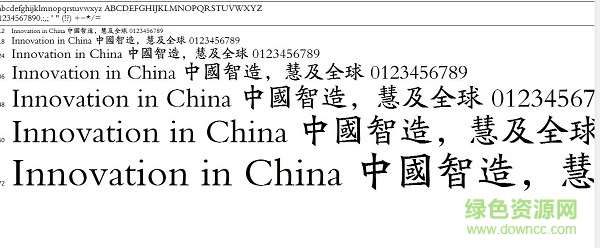
楷書繁體字體包
繁體楷書字體大全是本站為需要的朋友整理的楷書字體合集,包含了和平楷書、白舟細(xì)楷書、方正北魏楷書繁體、硬筆楷書繁體等一系列繁體字體,每一款制作都很不錯(cuò),適用范圍廣,有需要者歡迎免費(fèi)下載!
楷書介紹
【魏】
北派書體,帶著漢隸的遺型,筆法古拙勁正,而風(fēng)格質(zhì)樸方嚴(yán),長(zhǎng)于榜書,這就是所說的魏碑。南派書法,多疏放妍妙,長(zhǎng)于尺牘。
【唐】
唐代的楷書,亦如唐代國(guó)勢(shì)的興盛局面,真所謂空前。書體成熟,書家輩出,在楷書方面,唐初的虞世南、歐陽(yáng)詢、褚遂良、中唐的顏真卿、晚唐的柳公權(quán),其楷書作品均為后世所重,奉為習(xí)字的模范。
【宋元】
唐代楷書法度森嚴(yán)、結(jié)構(gòu)嚴(yán)謹(jǐn),到了宋元時(shí)期書法家們開始追求作品的美感,有的清秀俊朗,有的雍容典雅。